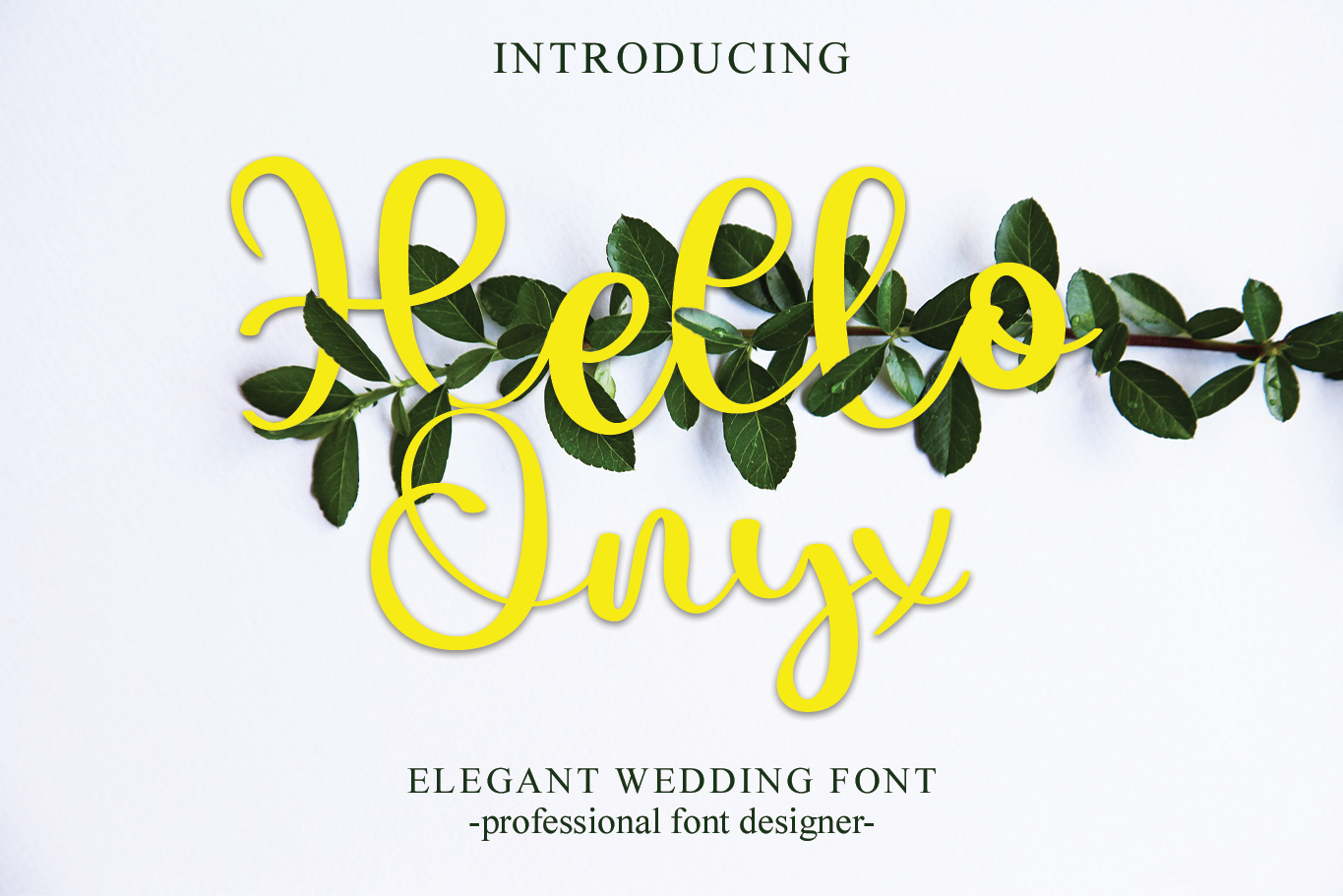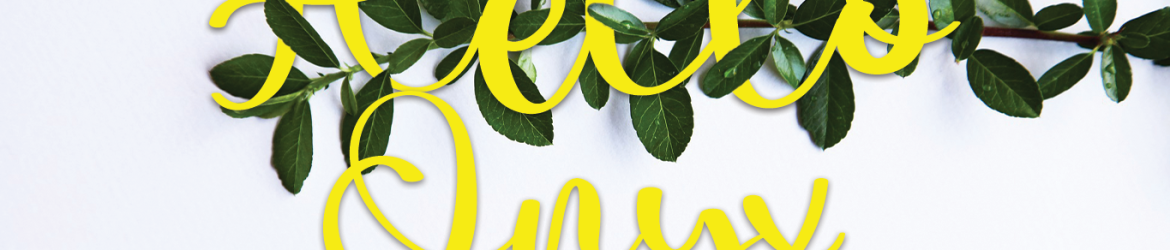
Hello Onyx Font – Download Grátis
A fonte “Hello Onyx Font” é uma elegante tipografia script que se destaca por seu trabalho meticuloso e detalhado. Ideal para quem busca uma ferramenta criativa e moderna para agregar valor a suas produções digitais, seja ela um projeto de design gráfico, uma publicação ou até mesmo uma página web. Esta fonte é perfeita para aqueles que desejam dar o toque final em seu trabalho, combinando sofisticação com facilidade de uso. Com “Hello Onyx Font”, você terá a oportunidade de personalizar seus projetos e deixá-los ainda mais impecáveis sem precisar de um designer profissional. Seja para criações digitais ou impressas, esta fonte oferece uma solução versátil e incrivelmente bonita que certamente será um ativo valioso em sua biblioteca de fonts.